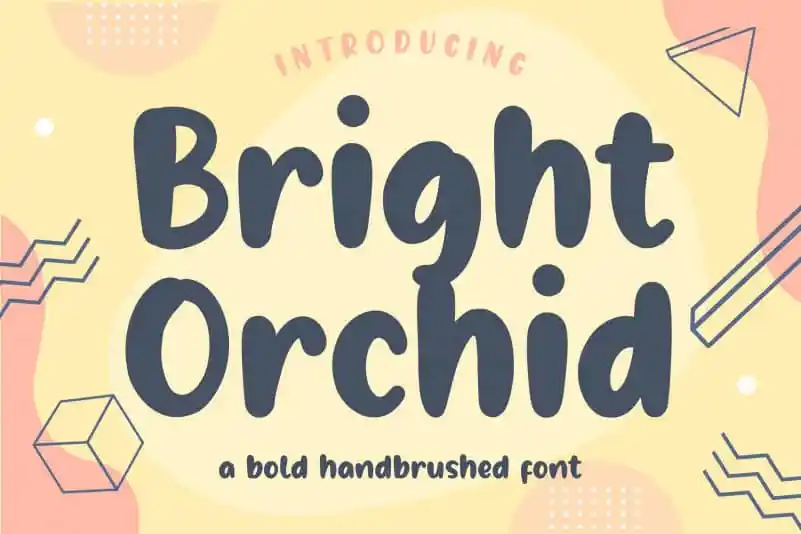
Bright Orchid Bold Handbrushed Font – Download Grátis
A fonte “Bright Orchid Bold Handbrushed Font” oferece uma experiência visual atraente e envolvente para qualquer projeto que você decida trazer para vida. Desenvolvida pelo designer balpirick, ela é perfeita tanto para aplicar em projetos de embalagem de produto ou marca, quanto para texturas de jornais e mídias sociais que buscam um toque autêntico e sofisticado. A combinação única entre a estrutura robusta da fonte bold com o estilo delicado da mão desenhada em branco, criam uma sensação quase artesanal. Este design elegante se destaca ainda mais sob fundos de texto ou imagens ricas, oferecendo um contraste sofisticado que pode ser usado para destacar mensagens importantes e personalizar textos em uma variedade de ambientes. Seja ela usada em cartões de casamento, materiais promocionais ou simplesmente para expressar letras acima do fundo – esta fonte é certamente um ativo valioso a qualquer designer gráfico.